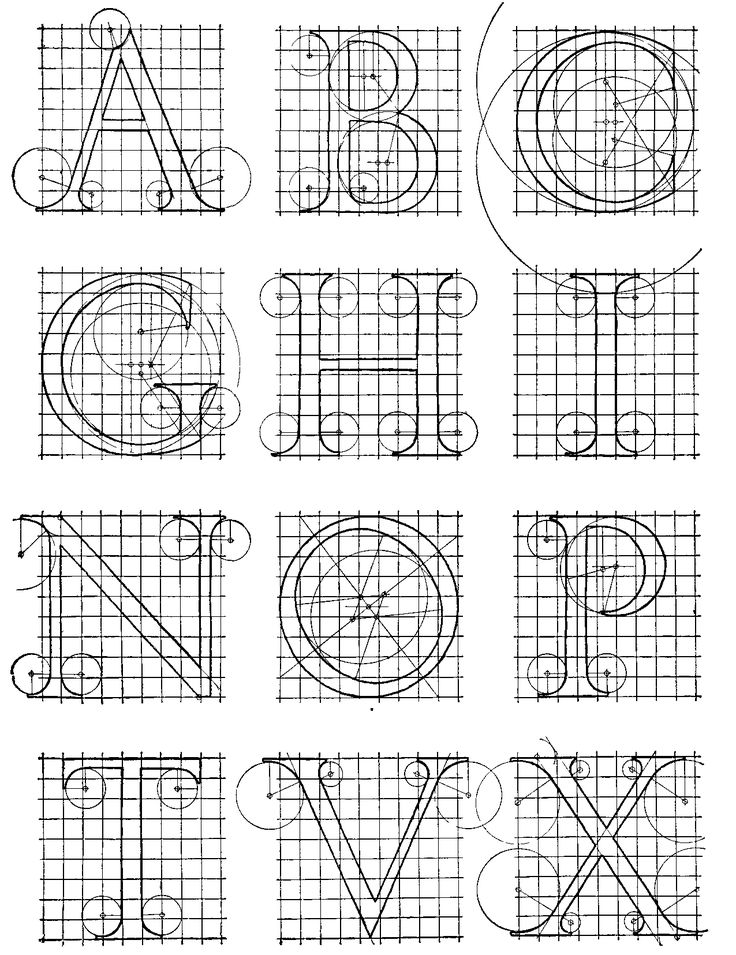
Шрифты для надписей на архитекту
В зависимости от способа выполнения надписей шрифты можно разделить на две основные группы — шрифты рукописные (чертежный) и шрифты, выполненные при помощи чертежных инструментов (шрифт зодчего, романский и др.). Для надписей на архитектурных чертежах (особенно на выставочных и конкурсных), на зданиях, архитектурных и инженерных сооружениях (год постройки, наименование объекта и т. д.), мемориальных досках, а также на заглавных листах инженерно-строительных чертежей применяются декоративные шрифты, относящиеся ко второй группе.
Из декоративных
шрифтов широкое распространение в архитектурных
и инженерно-строительных чертежах имеют шрифты
зодчего и романский,
которые относятся к категории вертикальных. |
ШРИФТ ЗОДЧЕГО Шрифт зодчего состоит из прописных, строчных букв и цифр. В зависимости от формы букв этот шрифт имеет несколько вариантов. Рассмотрим построение букв и цифр наиболее легкого варианта этого шрифта.
Прописные буквы шрифта
зодчего строятся в квадрате, сторона
которого равна b.
На рис. 1 показаны прописные буквы, шрифта зодчего, из которого легко можно уяснить конструкцию каждой буквы и ход ее построения. На рис. 2 дано построение строчных буке этого шрифта. |
Рис. 1 |
| Рис.1 | |||||||||||||||||||||||||||||||||||
| Рис.2 | |||||||||||||||||||||||||||||||||||
Из построения видно, что вся высота буквы с выступом делится на пять частей, причем высота основной части буквы принимается равной трем частям. Половина одного деления принимается за ширину основной стойки. Ширина тонкого элемента принимается равной 1/2 ширины основной стойки (рис. 2).
На рис. 3 дано
построение цифр шрифта зодчего. |
Рис.3 Рис.4 |
При построении шрифта зодчего необходимо помнить, что ошибка в чередовании широких и узких элементов является недопустимой, ибо сразу же нарушится стиль шрифта. Высота прописных букв шрифта зодчего при выполнении надписей принимается равной 1/20 — 1/30 высоты изображения. На рис. 4 дан пример выполнения надписи шрифтом зодчего. |
Рис.5 |
РОМАНСКИЙ ШРИФТ Романский шрифт вертикальный. По выполнению он является также довольно трудным. Буквы романского шрифта состоят из равномерно чередующихся широких и узких элементов, что объясняется потребностью ритма. Малейшее нарушение правильности этих сочетаний или форм элементов букв сразу же дает себя чувствовать.
Размер романского
шрифта определяется его высотой, принимаемой
равной примерно 1/20 высоты
изображения. Единицей измерения
элементов каждой буквы и цифры является модуль, представляющий
собой величину, равную 1/7 высоты шрифта. Все буквы и цифры шрифта по ширине можно разделить на 10 групп, представленных в табл. 1. Все широкие элементы букв и цифр по толщине обводки равны одному модулю. Узкие элементы букв и цифр не должны быть больше 1/4 — 1/3 модуля. Все элементы букв как широкие, так и узкие заканчиваются подсечками, выступающими, как правило, в каждую сторону на один модуль. Углы, образующиеся в подсечках, смягчаются дугами, обеспечивающими плавный переход.
Капли на концах узких элементов цифр
На рис.
6 показано начертание прописных букв и на рис.
7 — цифр романского шрифта с их относительными
размерами, из которого можно уяснить
конструктивные особенности
каждой буквы и цифры. |
Рис. |
| Рис.6 | |||||||||||||||||||||||||||||||||||
Рис.7 |
Таблица 1
Тщательное изучение конструкции букв и цифр романского
шрифта и практика их начертания обеспечат хорошее выполнение
надписей на архитектурных чертежах (фасадов зданий,
перспектив, генеральных планов и т. |
Шрифт зодчего — Стр 3
имеющая треугольную форму, служит «эталоном» для определения промежутков между другими буквами. Так, например, пробел между двумя буквами, ограниченными вертикальными стойками, должен быть примерно в два раза меньше расстояния между верхними точками двух рядом расположенных букв А (рис. 27).
| Промежутки между буквами округ- | |
1 |
| лого начертания также берутся несколько | |
| меньшими по сравнению с пробелами | |
| прямоугольных букв. | |
| деления промежутков между буквами соз- | |
2 |
| ||
| дает впечатление наиболее равномерного | ||
| их расположения. Размещение в надписи | |
Сторона квадрата делится на девять
частей, 1/3 часть
принимают за модуль т, одновременно модуль
является и шириной
основной стойки. Ширина тонких элементов
прописных букв принимается равной 1/3 модуля
Для удобства
построения квадрат разделен сеткой. Все построения строчных
букв и цифр подробно разработаны и дополнительных
объяснений не требуют.
п.).
Такой прием опре-